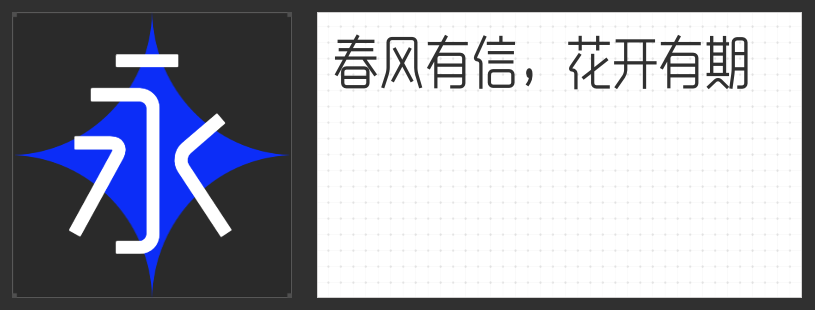
四款潮流字体推荐:解锁短视频设计的视觉爆点
短视频时代,字体不仅是信息传递的载体,更是塑造氛围、强化风格的关键元素。从动态标题到字幕弹幕,一款适配的字体能瞬间提升画面质感,让内容更具记忆点。本文精选四款风格鲜明的字库字体,涵盖稳重大气、古朴雅致、潮酷叛逆与谐趣动感,助你轻松打造吸睛短视频。
一、励字超级勇士简 微粗
作为通用黑体的升级版,励字超级勇士简 微粗通过外圆角设计打破传统黑体的生硬感,在笔画拐角处融入微弧曲线,既保留了黑体的稳重与屏显适配性,又增添了一丝灵动气息。其字面布局紧凑,中宫开阔,即使在小字号下也能保持清晰可读性,非常适合科技类、知识类短视频的标题与字幕设计,既能传递专业感,又避免视觉疲劳。
二、高手庆科静雅体 古朴版
这款字体以瘦长工整的字形为核心,通过均匀的布白与平稳的重心营造出古朴雅致的氛围。圆角处理贯穿始终——横竖笔画视觉等粗,转折处内外圆角过渡自然,小连笔设计让笔画软硬适中,既保留了书法的韵律感,又符合现代审美。适用于传统文化、历史解说类短视频,能瞬间提升内容的文化厚重感。
三、字恋狂拙黑简
专为年轻化场景打造的创意字体,字恋狂拙黑简以横细竖粗的纯直线笔画为基底,通过切口平直的笔形与中宫宽博的结构传递力量感,而连笔、连丝及手写化处理则赋予其叛逆不羁的潮酷气质。无论是游戏解说、音乐现场还是街头文化类视频,这款字体都能精准匹配Z世代的审美偏好,让标题成为画面的视觉焦点。
四、小豆岛惠中谐趣简繁
通过整体倾斜的结构与书法笔画的解构重组,小豆岛惠中谐趣简繁制造出一种“重心失衡”的活泼感,仿佛每个字符都在跳跃舞动。这种设计使其天然适配二次元、旅行Vlog、鬼畜搞笑等场景,既能强化画面的动态节奏,又能通过谐趣风格拉近与观众的距离,让字幕本身成为内容的一部分。
短视频设计需兼顾信息效率与视觉美感,而字体的选择往往是决定风格的关键。这四款字体各具特色,无论是追求专业屏显、文化底蕴、潮酷态度还是谐趣互动,都能为你的作品注入独特灵魂。